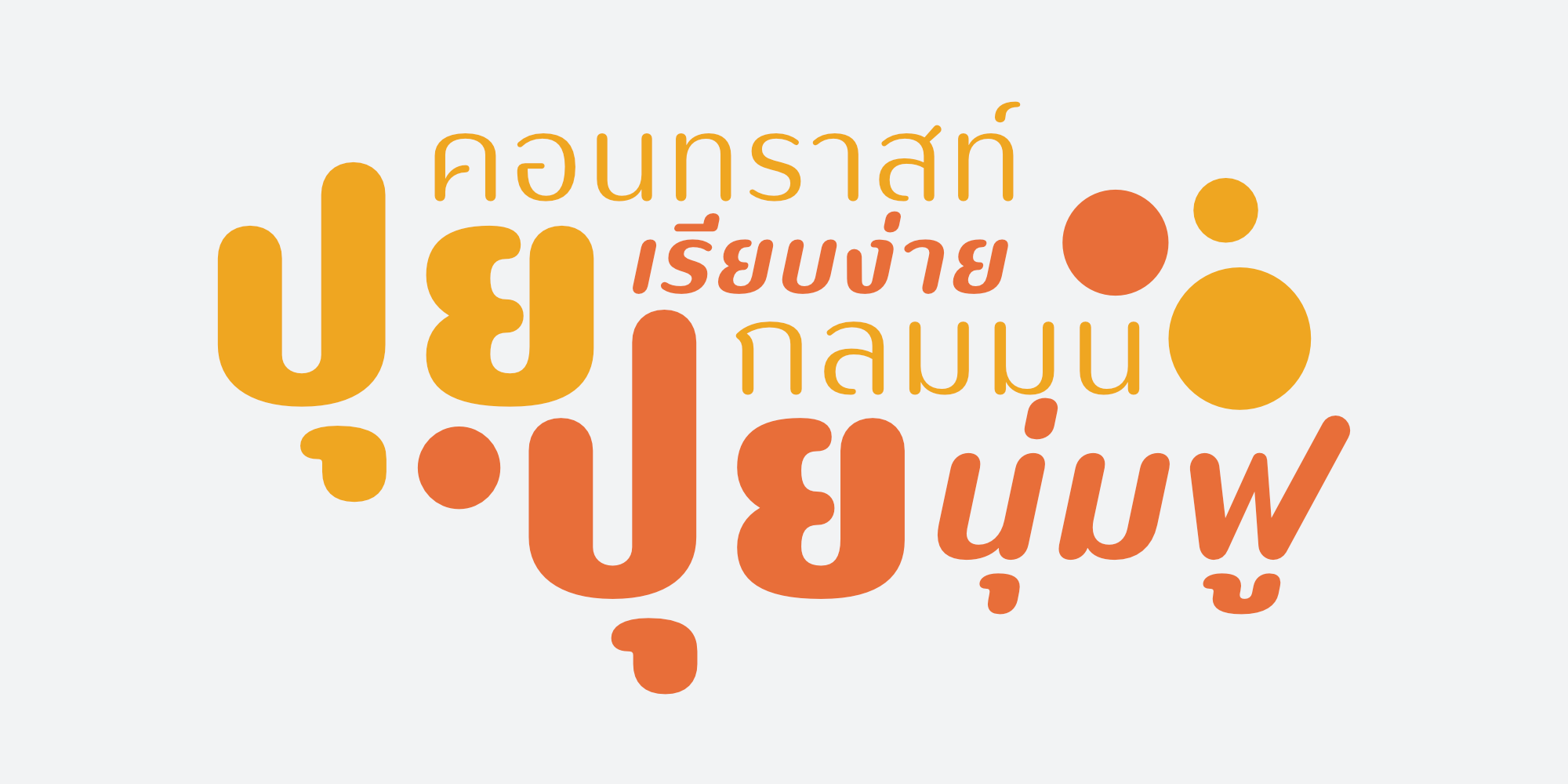
ปุยปุย | Puipui
ชื่อ ปุยปุย | Puipui
ขื่อฟอนต์ : ปุยปุย | Puipui
ฟอนต์ปุยปุย เป็นอักษรแบบแซนเซอริฟที่มีความมน มีคอนทราสของเส้น ดูเรียบง่าย มีทั้งหมด 9 น้ำหนักและตัวเอียงของแต่ละน้ำหนักรวมทั้งหมดมี 18 สไตล์ รองรับหลายภาษาและภาษาไทย เหมาะสำหรับการใช้ผาดหัวหรือตัวเนื้อความ ฟอนต์ปุยปุยสามารถช่วยส่งเสริมมูทแอนโทนให้ดูน่ารักยิ่งขึ้น เหมาะกับสินค้าที่เกี่ยวข้างกับเด็ก, สัตว์เลี้ยง, อาหาร หรือคอนเทนท์ที่ต้องการความน่ารัก
Puipui is a sans serif typeface with a rounded, contrast stroke and minimal look. Comes with 9 weights and italics of each weight total 18 styles. Support multi-languages and Thai language. Suitable for Headline or text body. Puipui can help you to create a mood and tone of cuteness suitable for kid, pet, food product or anything about cuteness content.